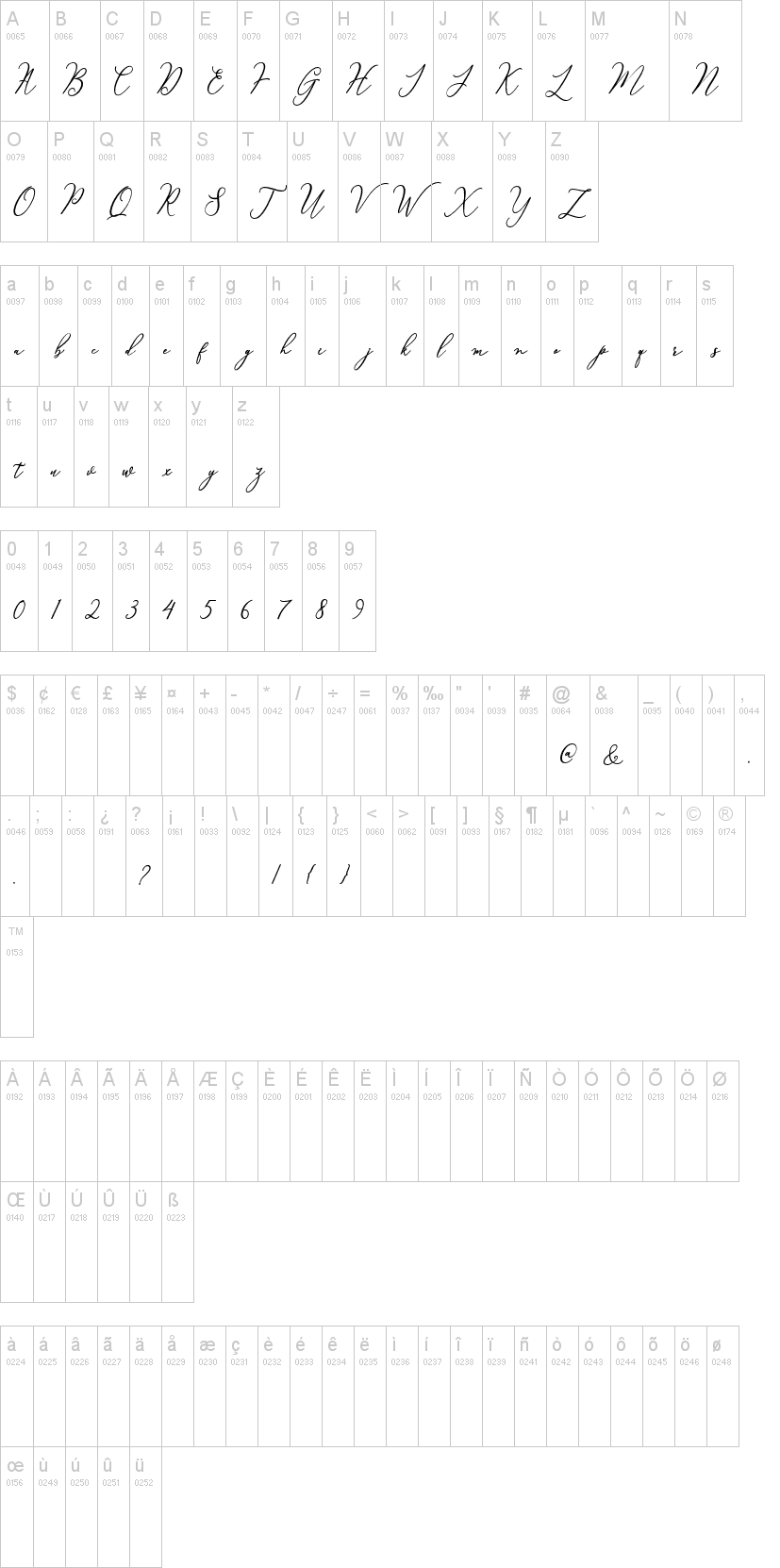
Courtney
Courtney字体是一款比较特别的字体,它的特点是结构简洁、笔画细腻,字体的线条细腻,有着柔和的曲线,使字体看起来更加优雅高贵。它的字形大多是圆润的,有着清新的外形,可以用来做标题、标签等。Courtney字体适合用于品牌标志、商标、海报、网站等场景,可以让您的设计更加精致、有个性。
Courtney是一款非常不错的手写艺术字体,具有很好的视觉感,适合于文化类的宣传设计、商业类品牌的广告和产品包装设计以及个性化文字排版等较多场景。
Courtney字符映射图